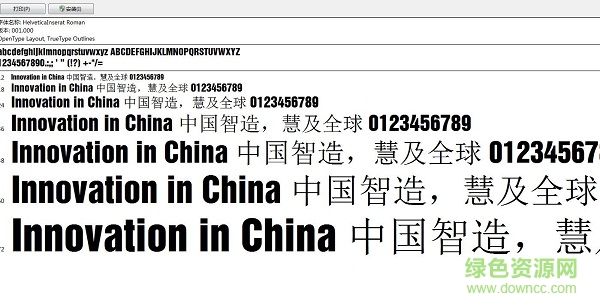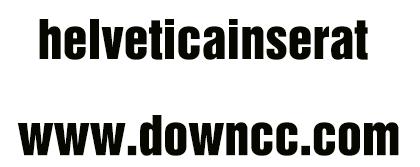
helveticainseratl tstd roman字體是一款不錯(cuò)的無襯線字體,線條粗非常醒目,有陽剛之氣,可以用作標(biāo)題或者海報(bào)標(biāo)語,有需要者歡迎在本站免費(fèi)下載!
Roman指的就是襯線體,這個(gè)稱呼是因?yàn)橐r線的起源于羅馬時(shí)期的碑刻。由于通常都把襯線體作為正文字體,所以很多場合下,Roman 就變成了正文字體的代名詞。